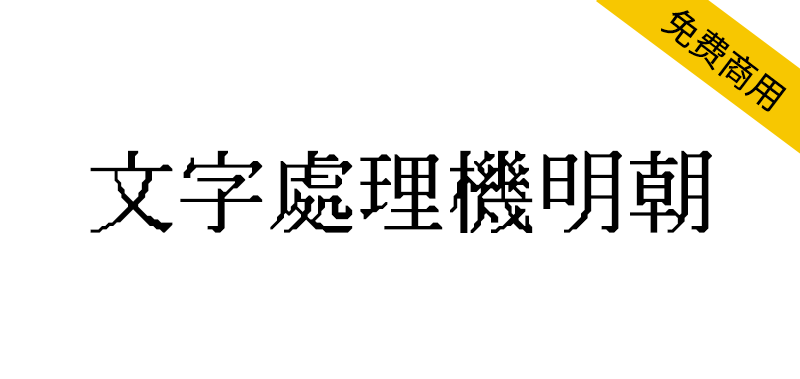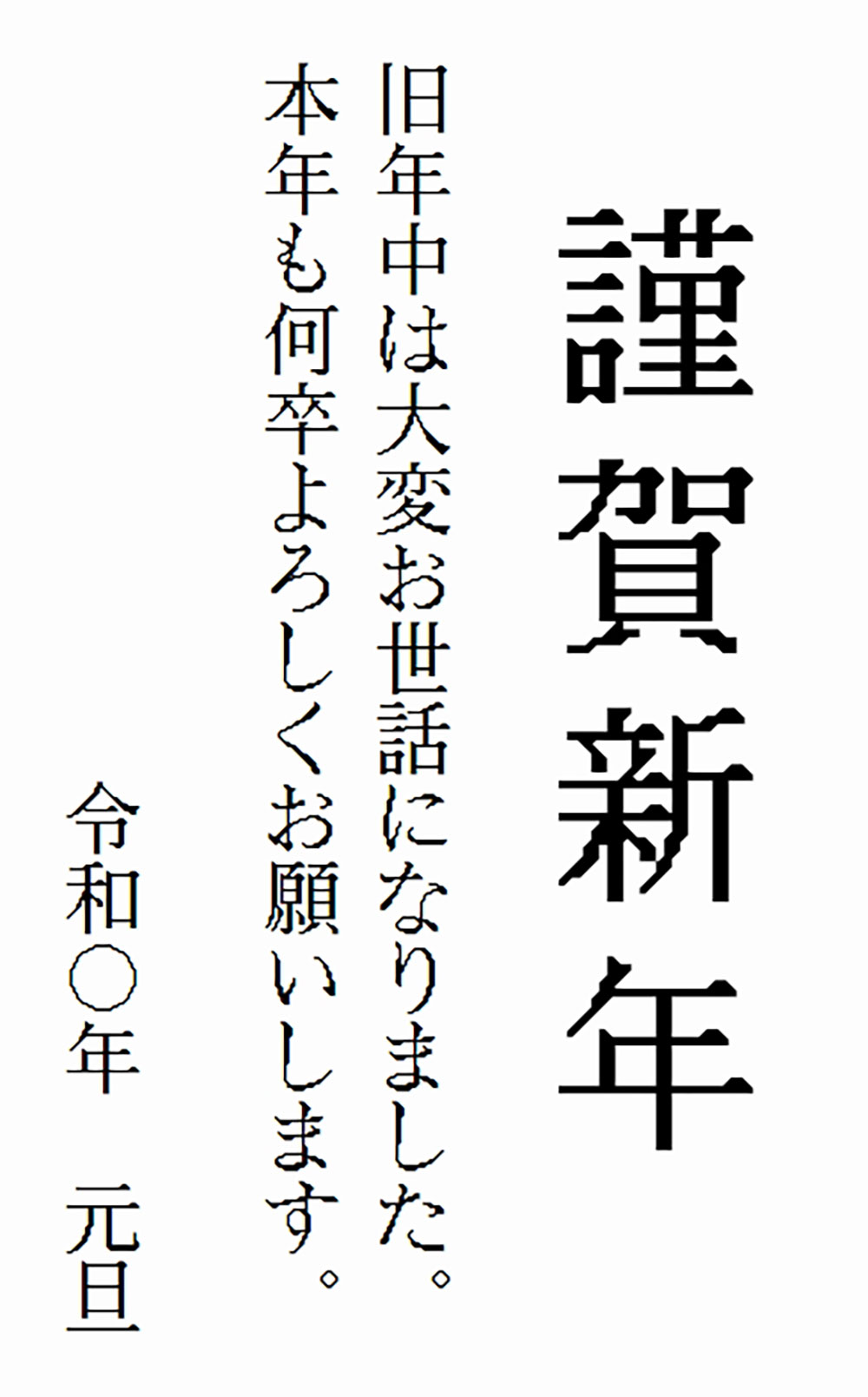
文字处理机明朝体(ワープロ明朝)是一款模拟日本上世纪80年代至90年代初文字处理机(ワープロ専用機)中使用的点阵字体放大效果的字体。
在文字处理机的后期机型中,虽然已搭载轮廓字体(アウトラインフォント)并能实现平滑放大,但早期设备在打印大字号时仍需将点阵字体(ビットマップフォント)强制放大。直接放大会导致文字边缘出现锯齿,因此通过斜线插值算法对阶梯状像素点进行补间处理,从而形成独特的视觉风格。
本字体以24点像素点阵明朝体(jiskan24)为基础,经上述插值处理后转换为轮廓字体,重现了复古的数字排版质感。
「ワープロ明朝」は、1980年代〜90年代初めのワープロ専用機などで使われていた、ビットマップフォントの拡大処理を再現したフォントです。
ワープロ専用機も後期にはアウトラインフォントが搭載されて綺麗な拡大が可能になりましたが、それ以前は大きな文字を印刷するときにもビットマップフォントを拡大して使っていました。そのまま拡大するとギザギザになってしまうので、階段状になったドットを斜めの線で補間する処理が施されて独特な見た目になっていました。
「ワープロ明朝」は24ドットの明朝体ビットマップフォント jiskan24 にこの補間処理を行い、アウトラインフォント化したものです。